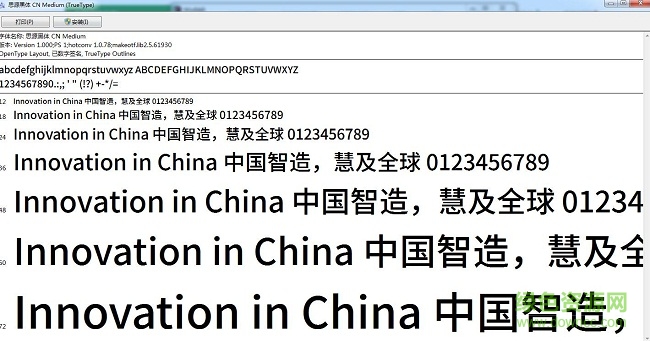
sourcehansanscn mediumgbpceuch字體又叫思源黑體cn medium-中,是一款由Adobe公司開發(fā)的黑體字體,同時支持中英文顯示,粗細(xì)勻稱,轉(zhuǎn)角處理精致,需要的朋友快來下載吧!
“黑體”是一類字體的總稱,有很多字體都屬于這個范疇,特點是沒有襯線裝飾,筆劃粗壯有力,撇捺等筆畫不尖,使人易于閱讀,由于其醒目的特點,常用于標(biāo)題,導(dǎo)語,標(biāo)志等等。